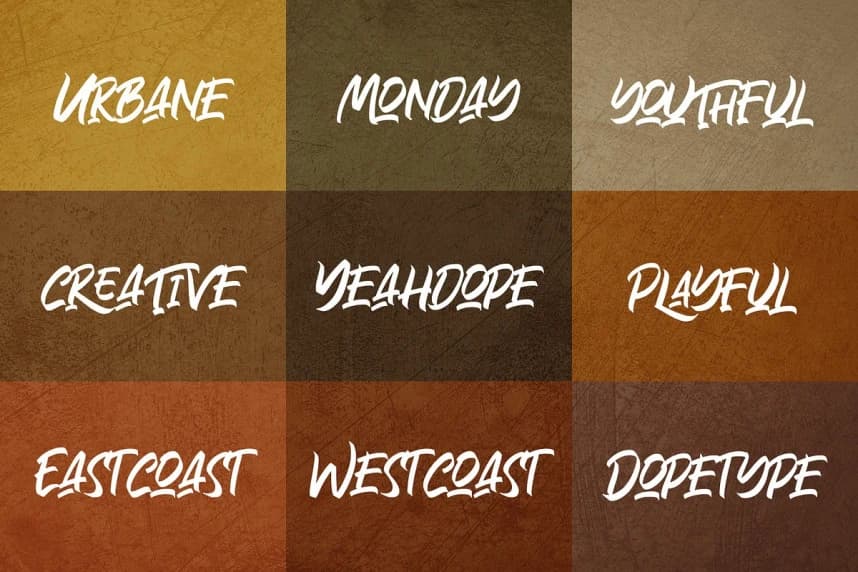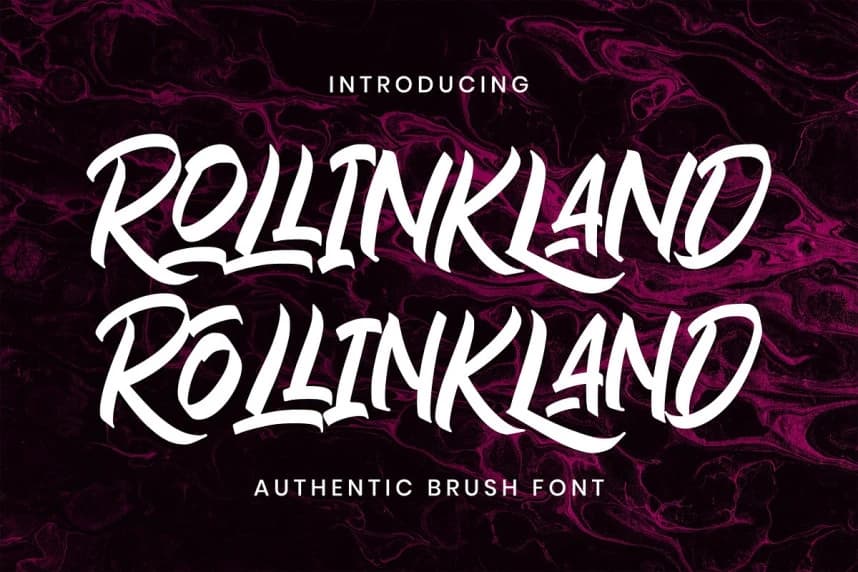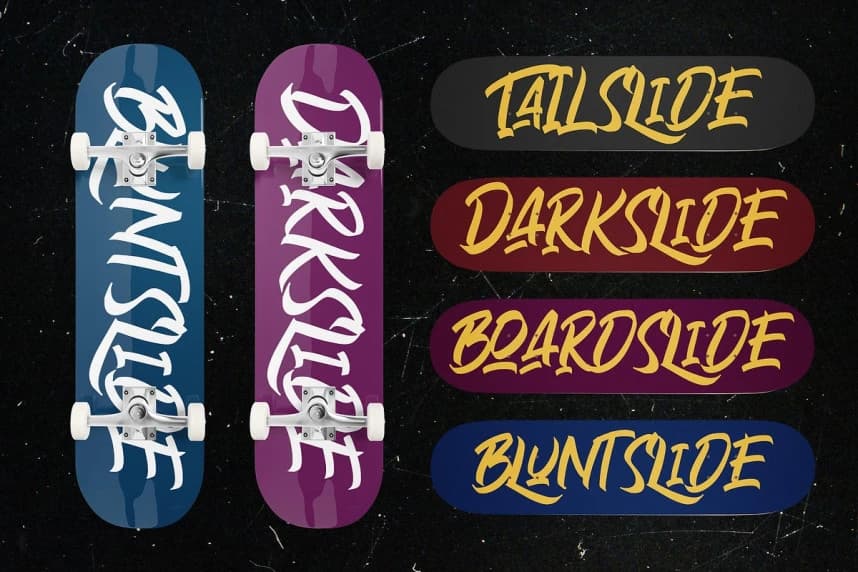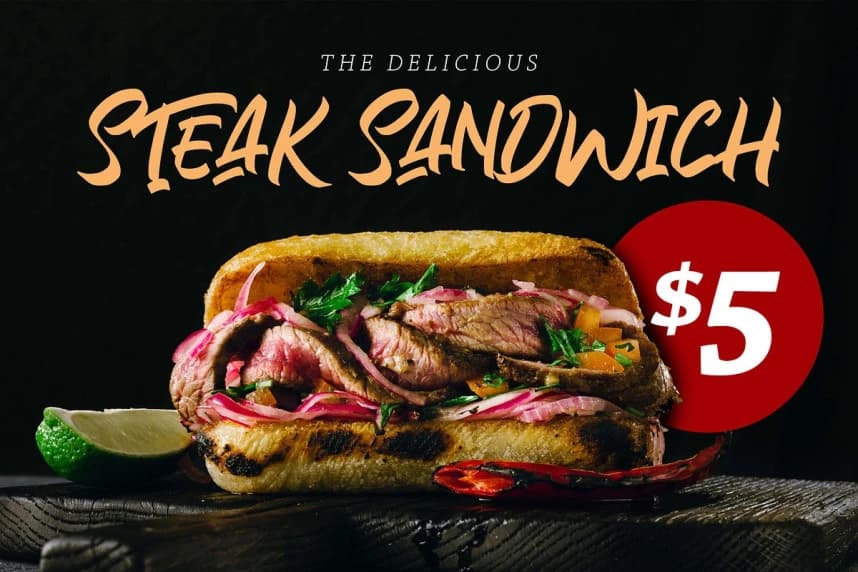
Rollinkland Font
Rollinkland Font, net bir stile ve dramatik hareketlere sahip otantik bir fırça yazı tipidir. Bu yazı tipi, bir sonraki yaratıcı projeniz için harikadır; örneğin logolar, basılı alıntılar, davetiyeler, kartlar, ürün ambalajı, başlıklar, logotip, antet, afiş, giyim tasarımı, etiket ve benzeri için.
Rollinkland Font, net bir stile ve dramatik harekete sahip otantik bir fırça yazı tipidir; bu yazı tipi bir sonraki yaratıcı projeniz için harikadır; örneğin logolar, basılı alıntılar, davetiyeler, kartlar, ürün ambalajı, başlıklar, logotip, antet sayfası, afiş, giyim tasarımı, etiket ve benzeri.